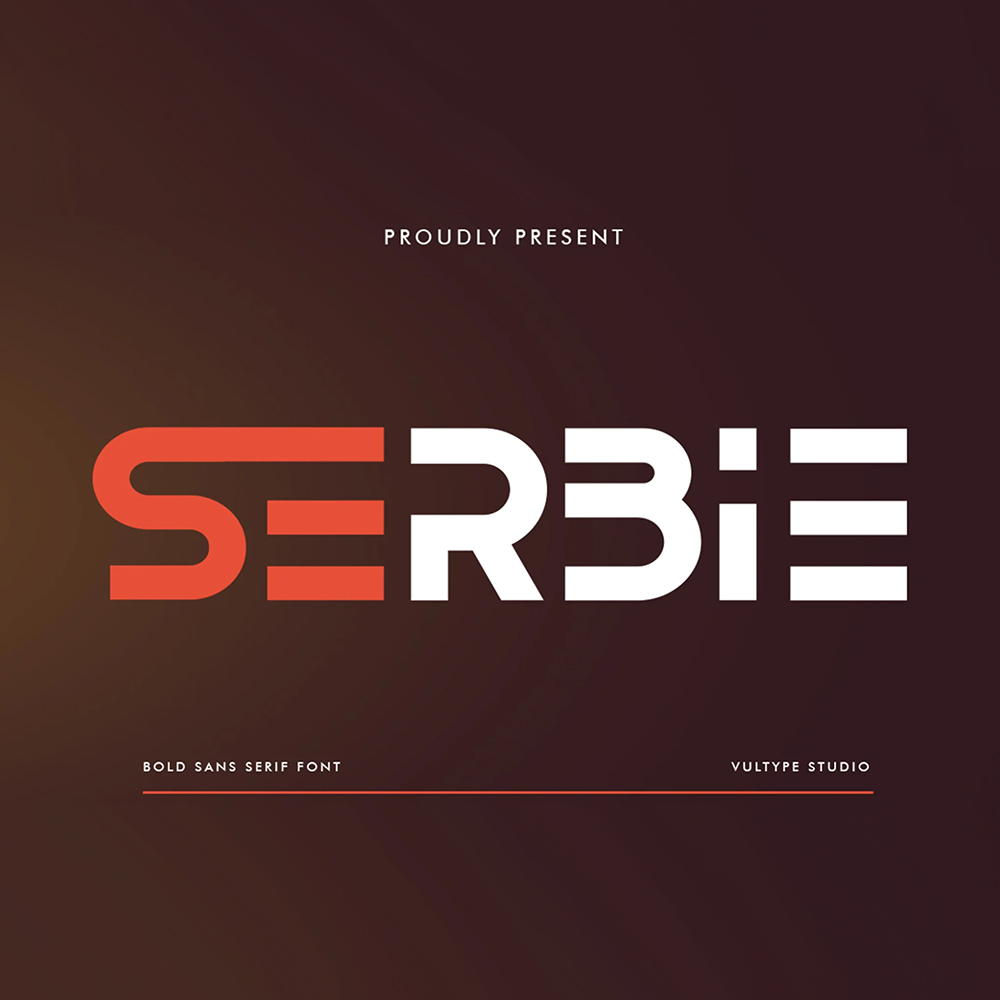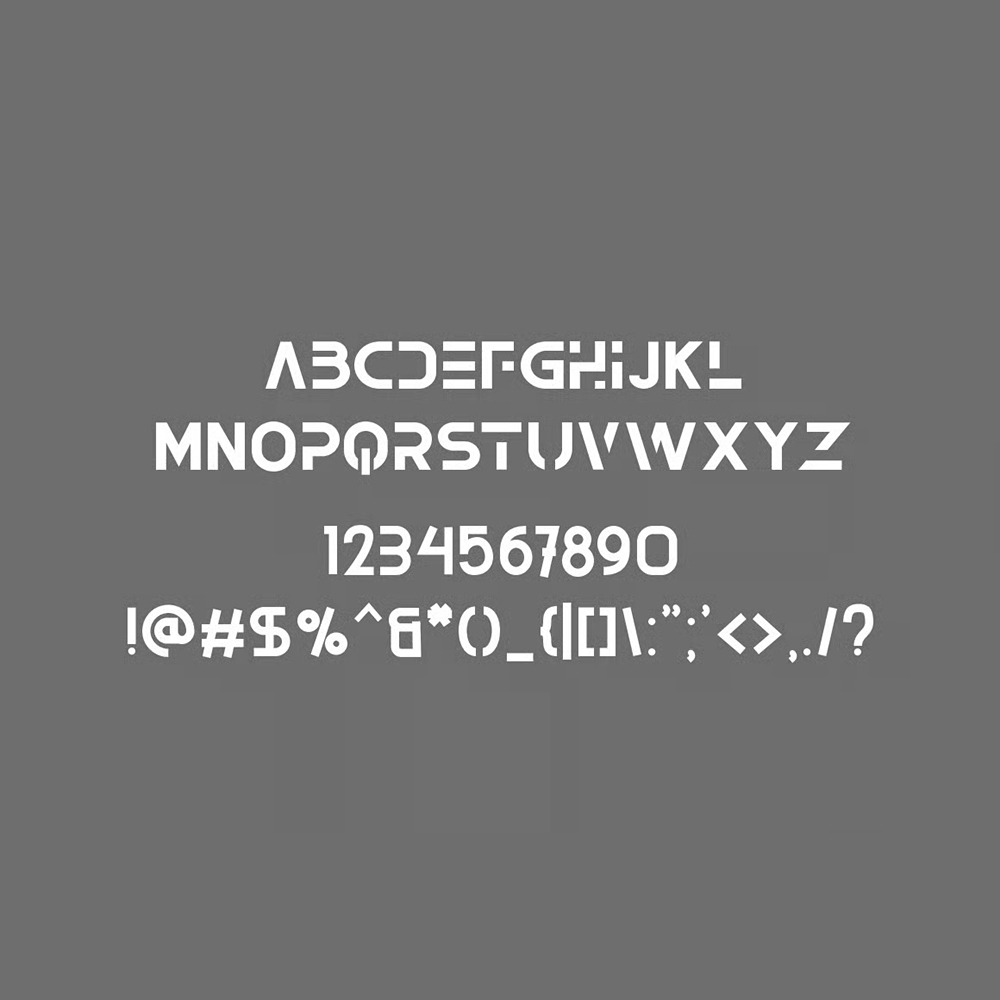
دانلود فونت انگلیسی Serbie Font
فونت پرمیوم و انگلیسی Serbie یک فونت بر پایه سنس با حروف کوچک منحصر به فرد است که طراحی شما را آیندهنگر و مدرن جلوه میدهد. از این فونت میتوانید برای هر منظوری، به خصوص برای ساخت لوگوتایپ، استفاده کنید.
مزایای استفاده از فونت لاتین Serbie Font چیست؟